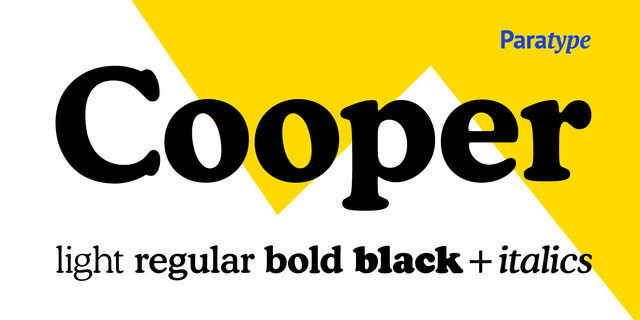
ПТ BT Купер Гарнитура разработана в 1986 году в фирме Bitstream на основе шрифта Cooper Black (1919, дизайнер Освальд Купер), к которому были доработаны более светлые начертания. Cooper Black был впервые выпущен как ручной шрифт чикагской фирмой Barnhart Brothers & Spindler в 1922 году, а затем распространялся фирмой American Typefounders/ATF. В основе его рисунка лежит сверхжирная версия гарнитуры Cooper Old Style. Bitstream Cooper - это антиква старого стиля с закругленными засечками и с наклоном осей овалов влево. Предназначен как для набора текста (светлые начертания), так и для рекламы и акциденции (жирные начертания). Кириллическая версия разработана для фирмы ParaType в 2000 году (дизайнер Манвел Шмавонян) на основе рисунков гарнитуры TM Osvald фирмы TypeMarket (1996, дизайнер Виктория Григоренко).
Ассоциации c начертанием Cooper BlackКачества и характер:
убедительный, увесистый, тяжелый, щедрый, обильный, изобильный, насыщенный, вкусный, пышный, мягкий, спокойный, комфортный, дружелюбный, уютный, добрый, приятный, доброжелательный, гладкий, пластмассовый, детский, наивный, мультяшный, толстый, семейный, заметный, яркий, активный, броский, домашний, пухлый
еда, торговля, реклама, аптека, молоко, сыр, десерт, дом, мебель, игрушка, мультфильм, кондитерская, сладости, выпечка, булочки, булочная, мороженное, детская книжка, раскраска, кафе, игра, мягкая игрушка, анимация, семья, кофе, обед, ужин, смузи, соус, сметана, кетчуп, жвачка, подгузник, чипсы Стилистика:
— Особенности семейства CooperХит десятилетия:
Хит 1960-х Хит 1970-х Этот шрифт в логотипах:
Cooper Black, Cooper Old Style, TM Osvald